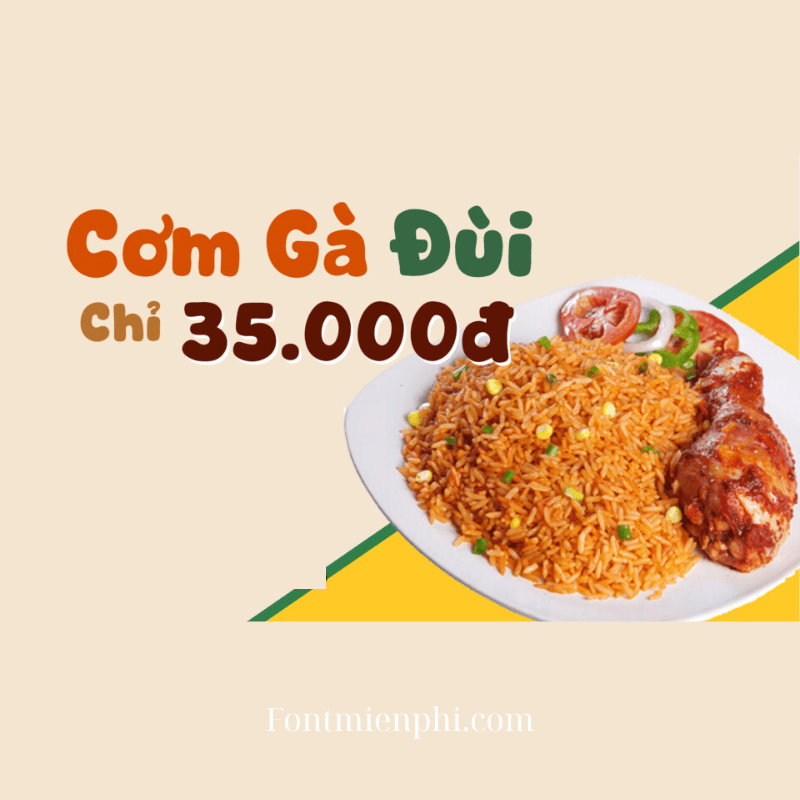
Font Việt hóa 1FTV VIP Cute Dino
Font Việt hóa 1FTV VIP Cute Dino – Bộ Font Chữ Khủng Long Siêu Đáng Yêu Cho Bé
Giới thiệu về Font Việt hóa 1FTV VIP Cute Dino
Trong thế giới thiết kế dành cho trẻ em, việc lựa chọn một Font Miễn Phí phù hợp đóng vai trò cực kỳ quan trọng để tạo nên sự thu hút. Font Việt hóa 1FTV VIP Cute Dino là một lựa chọn hoàn hảo mang phong cách vui nhộn và tinh nghịch. Lấy cảm hứng từ hình ảnh những chú khủng long tí hon, bộ font này mang đến cảm giác gần gũi và đầy sáng tạo cho mọi khung hình. Với các đường nét bo tròn mềm mại, đây không chỉ là một bộ chữ thông thường mà còn là linh hồn cho các dự án thiết kế giáo dục hiện nay.
Tại sao nên chọn Font Việt hóa 1FTV VIP Cute Dino?
Đặc điểm nổi bật nhất của Font Việt hóa 1FTV VIP Cute Dino chính là sự thân thiện với người dùng Việt. Font đã được xử lý dấu tiếng Việt kỹ lưỡng, giúp các thầy cô giáo và phụ huynh dễ dàng soạn thảo tài liệu học tập mà không lo lỗi hiển thị. Kiểu dáng chữ đầy đặn, chân thực giúp các bạn nhỏ dễ dàng nhận diện mặt chữ, từ đó kích thích niềm đam mê đọc sách và học hỏi ngay từ khi còn bé.
Ứng dụng thực tế của bộ font trong học đường
Sáng tạo bài giảng và trang trí lớp học
Font Việt hóa 1FTV VIP Cute Dino rất phù hợp để thiết kế tiêu đề bài giảng PowerPoint, làm bảng tên học sinh hoặc thiệp mời sinh nhật. Ngoài ra, các nhà thiết kế có thể sử dụng font này để in ấn lên áo thun, ly sứ hoặc làm decal dán tường trong phòng ngủ của bé. Sự linh hoạt này giúp bộ font trở thành công cụ đắc lực cho các chiến dịch marketing hướng đến đối tượng trẻ thơ.
Kết luận về bộ font chữ độc đáo này